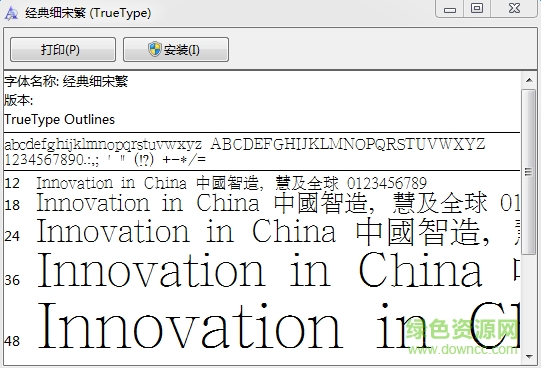
經(jīng)典細(xì)宋繁
經(jīng)典細(xì)宋繁是一款很不錯(cuò)的電腦繁體字體,這款字體最大的的特點(diǎn)就是比較細(xì),用于書(shū)畫(huà)寫(xiě)作或者是在書(shū)畫(huà)上題字題詞都是很不錯(cuò)的,喜歡這款字體的朋友可以來(lái)綠色資源網(wǎng)下載。